وقتی مطلب «فونتهای مناسب تامنیل یوتیوب» رو خوندم، برام جالب بود؛ اما احساس کردم با واقعیت چیزی که سالها در طراحی تامنیل تجربه کردم فاصله داره. همین باعث شد تصمیم بگیرم تجربه و نگاه خودم رو درباره جایگاه واقعی فونت در طراحی تامنیل با شما به اشتراک بزارم.
تامنیل در یوتیوب نقش جلد یک کتاب را دارد؛ اولین چیزی که توجه مخاطب را جلب میکند و او را به کلیک کردن ترغیب میکند. از آنجا که کاربران هنگام مرور صفحه اصلی یا بخش پیشنهادها تنها چند ثانیه برای تصمیمگیری زمان دارند، تامنیل به اولین نقطه ارتباط میان محتوا و مخاطب تبدیل میشود. یک تامنیل موفق تنها زیبا نیست؛ بلکه باید مفهوم ویدئو را بهسرعت منتقل کند، احساس ایجاد کند و کنجکاوی مخاطب را برانگیزد. به همین دلیل، تامنیل بخشی مهم از استراتژی جذب مخاطب و افزایش بازدید در یوتیوب محسوب میشود.
فونت؛ فراتر از یک عنصر تزئینی
فونت در تامنیل تنها یک عنصر تزئینی نیست، بلکه یکی از مهمترین ابزارهای ارتباط با مخاطب است. یک فونت مناسب به انتقال سریع پیام کمک میکند، حس و لحن محتوا را پیش از خواندن متن به مخاطب منتقل میکند و نگاه او را به مهمترین بخش تامنیل هدایت میکند.علاوه بر این، استفاده مداوم از یک سبک مشخص فونت میتواند به شکلگیری هویت بصری کانال کمک کند و باعث شود مخاطبان محتوا را سریعتر تشخیص دهند. به همین دلیل، انتخاب فونت در طراحی تامنیل بخش مهمی از استراتژی جذب مخاطب و برندسازی محسوب میشود.
ویژگیهای فونت مناسب برای تامنیل یوتیوب
خوانایی مهمترین معیار در انتخاب فونت برای تامنیل است. از آنجا که بیشتر کاربران تامنیلها را در ابعاد کوچک و روی تلفن همراه مشاهده میکنند، متن باید در نگاه اول واضح و قابل خواندن باشد. عواملی مانند ضخامت مناسب فونت، فاصله استاندارد بین حروف و کلمات، و کنتراست کافی میان متن و پسزمینه نقش مهمی در افزایش خوانایی دارند. همچنین استفاده از عناصری مانند سایه یا استروک میتواند به دیده شدن بهتر متن کمک کند. در نهایت، هرچه متن سادهتر و سریعتر خوانده شود، احتمال جلب توجه مخاطب و تعامل او با محتوا بیشتر خواهد بود.
نمونههایی از استفاده فونت در تامنیلهایی که دیزاین کردم.
در بحث انتقال پیام، فونت ادامه یکی از نمونههای مناسب به شمار میرود. این فونت با حفظ خوانایی و وضوح، پیام را بهسرعت به مخاطب منتقل میکند و در عین حال از هویت بصری مشخصی برخوردار است. به همین دلیل، میتواند نمونهای از فونتی باشد که فراتر از یک عنصر تزئینی عمل کرده و نقش مؤثری در ارتباط با مخاطب ایفا میکند.
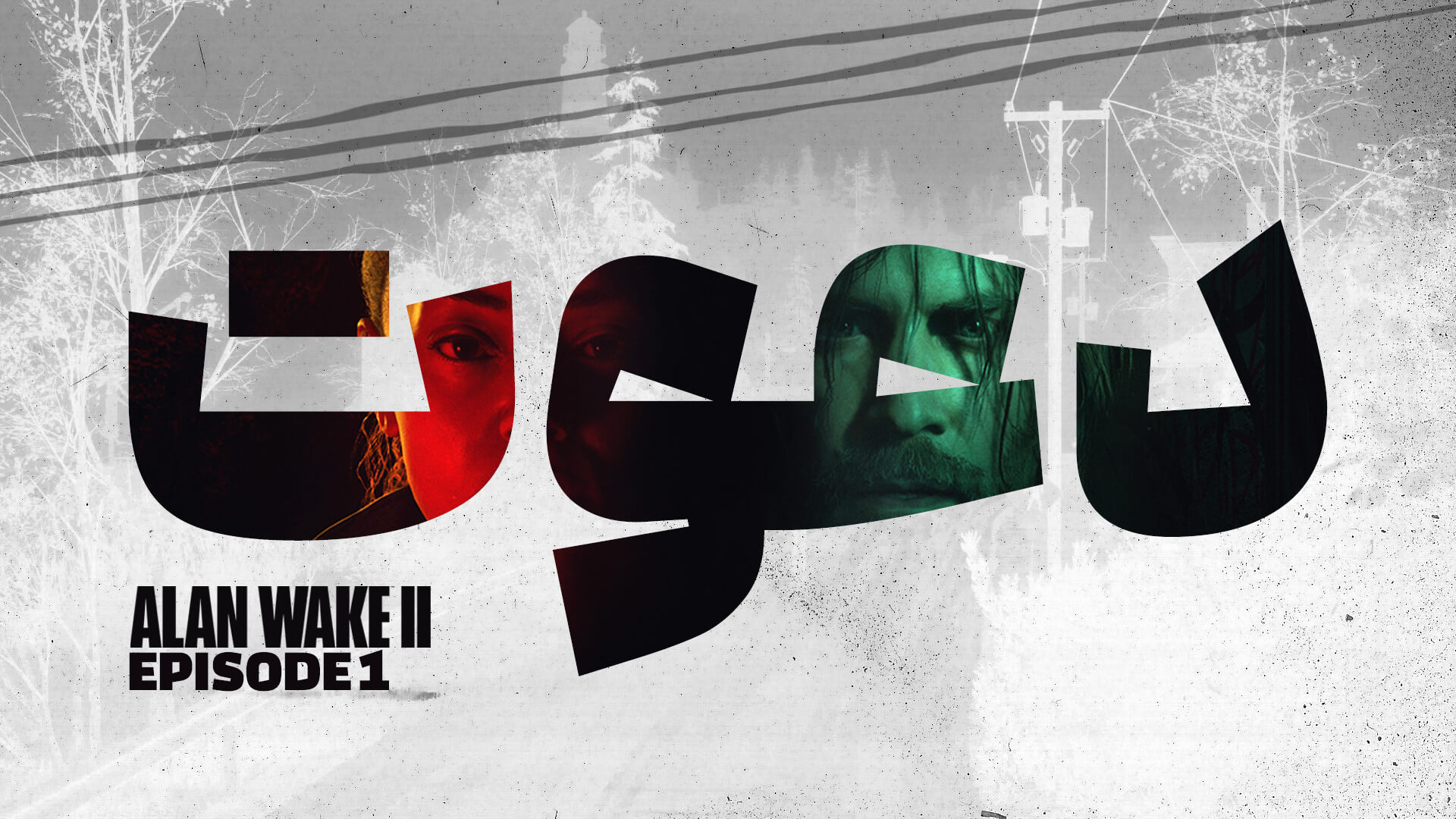
برای کانال یوتیوب کامپیوترکا KomputerKa ، فونت ادامه انتخاب شد، زیرا با لحن روایت و شخصیت محتوای کانال هماهنگی بالایی دارد. این کانال بر انتقال سریع و مستقیم پیام تمرکز دارد و به همین دلیل به فونتی نیاز داشت که بدون پیچیدگی، مفهوم را در کوتاهترین زمان ممکن به مخاطب منتقل کند.برای مثال، در اپیزود نخست با موضوع Alan Wake از کلمه «دعوت» استفاده شد. وزن و ساختار فونت ادامه باعث شد این کلمه بهسرعت دیده شود و تأثیر اولیه موردنظر را ایجاد کند. به همین دلیل، مهمترین معیار در انتخاب این فونت، توانایی آن در انتقال سریع و مؤثر پیام بود.
چه محتوای ویدئو فضایی جدی و تاریک داشته باشد و چه پرانرژی و هیجانانگیز باشد، فونت ادامه میتواند هویت بصری یکپارچه کانال را حفظ کرده و پیام را بهسرعت به مخاطب منتقل کند. نمونههای بیشتر این رویکرد را میتوان در کانال KomputerKa مشاهده کرد.
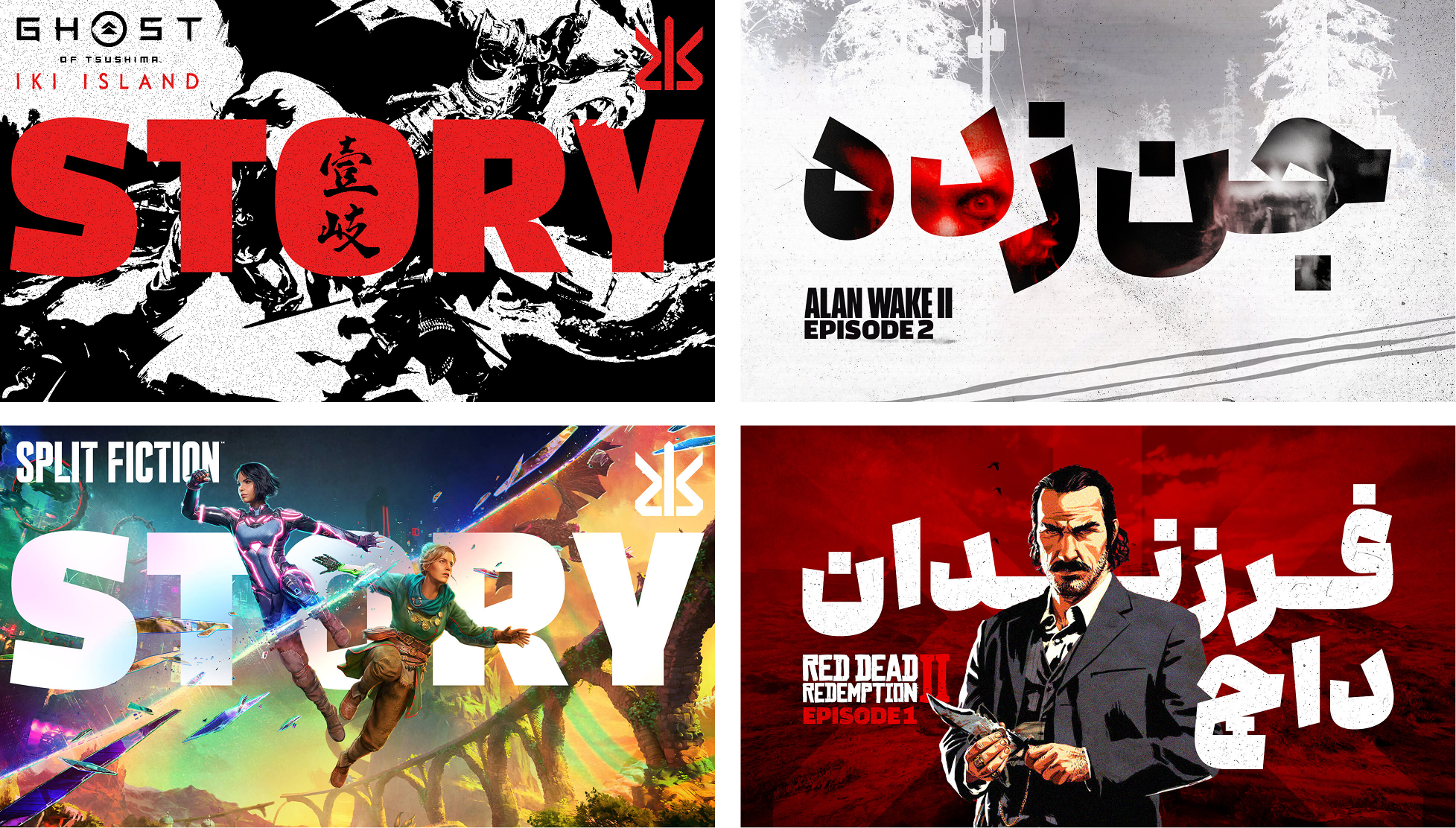
پیش از بررسی کانالهای دیگر یوتیوب، بد نیست به یک نمونه از نقش فونت در برندسازی نگاه کنیم؛ استفاده از سه فونت کلمه، انجمن، ادامه اما با موضوع بازی Alan Wake.
با وجود یکسان بودن موضوع محتوا، هر کانال با انتخاب فونت متفاوت توانسته هویت بصری مخصوص به خود را شکل دهد. این موضوع نشان میدهد که فونت، فراتر از یک ابزار نوشتاری، میتواند نقش مهمی در تعریف شخصیت و هویت یک محتوا داشته باشد.
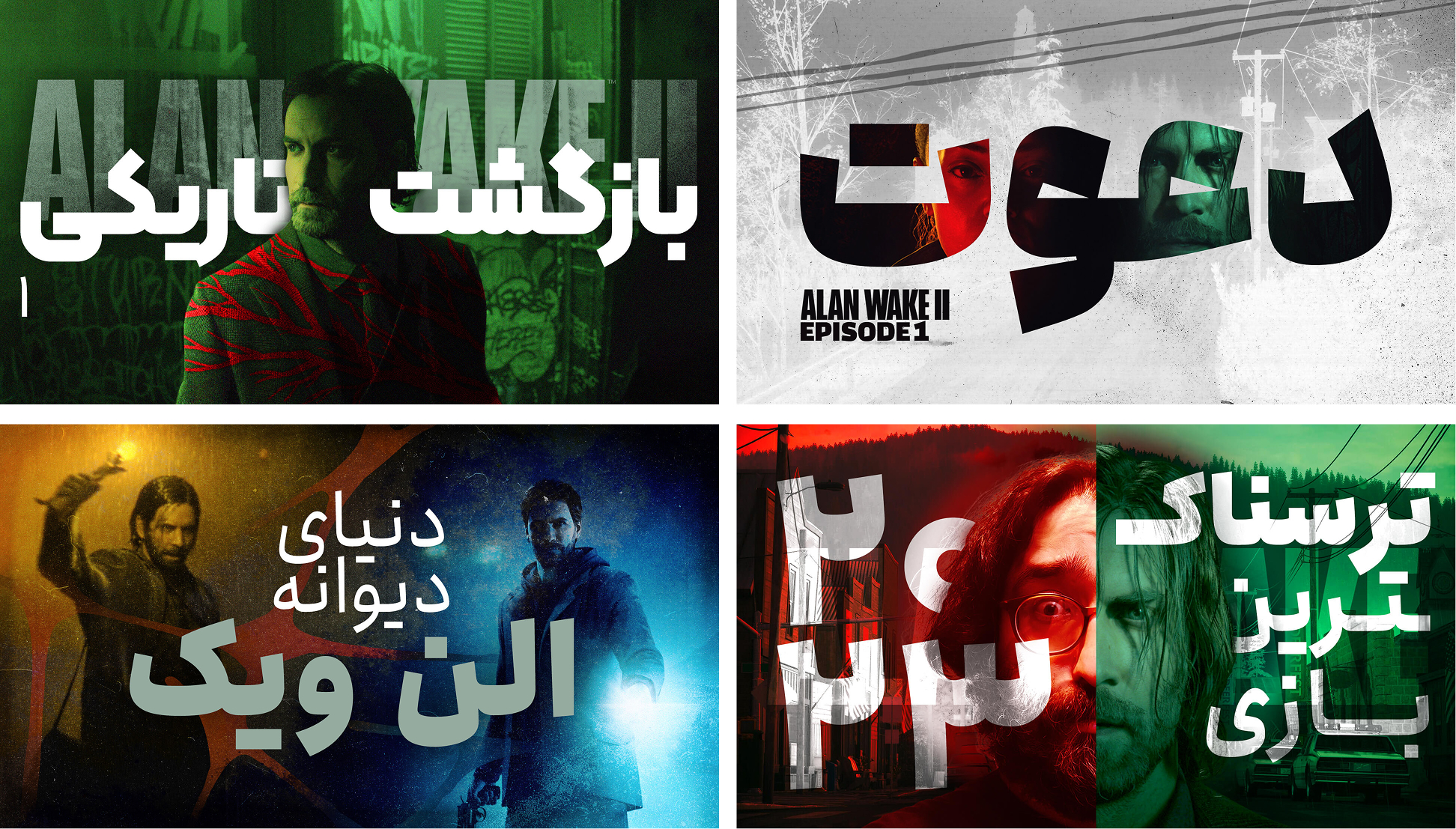
برای کانالهای یوتیوب Omid Lennon و KasraKT از فونت انجمن استفاده شده است. دلیل این انتخاب بیشتر به جنس محتوای این دو کانال برمیگردد؛ زیرا کسری کریمیطار و امید صدیقایمانی پیش از تولید محتوا در یوتیوب، سالها در حوزه نقد، مقالهنویسی و بررسی حرفهای بازیهای ویدیویی فعالیت داشتهاند.
فونت انجمن بهدلیل تنوع وزن و ساختار متعادل خود، انتخاب مناسبی برای این سبک محتواست. این فونت کمک میکند بخشهای مهم متن تأکید بیشتری بگیرند و در مقابل، بخشهای کماهمیتتر با وزن سبکتر نمایش داده شوند. در نتیجه، مخاطب راحتتر میتواند سلسلهمراتب اطلاعات را تشخیص دهد و روی نکات اصلی تمرکز کند.این ویژگی باعث شده «انجمن» علاوه بر حفظ خوانایی، با فضای تحلیلی این دو کانال نیز هماهنگی خوبی داشته باشد.
پس از بررسی و آزمون گزینههای مختلف، در همکاری با کانال یوتیوب THE PLAY MIND به این جمعبندی رسیدیم که فونت درباره بهترین انتخاب است؛ چرا که بیش از هر گزینهی دیگر، توانست فرم بصری و نگاه مدنظر ما را بهدرستی منتقل کند.
در فرآیند انتخاب فونت برای کانال یوتیوب AMIRFERY، بهدنبال فرمی بودم که بتواند بهصورت همزمان حس بازیگوشی و استحکام را منتقل کند. پس از بررسی گزینههای مختلف، فونت کلمه تنها گزینهای بود که توانست این دو ویژگی را برای ما بهدرستی در کنار یکدیگر به نمایش بگذارد.
در کانال یوتیوب Masoudbyhimself، مسعود تیموری پیش از آغاز همکاری با من، فونت دانا را بهعنوان فونت اصلی کانال انتخاب کرده بود. این انتخاب، بهدلیل خوانایی بالا و شخصیت بصری منسجم، بستر مناسبی برای توسعه هویت بصری کانال ایجاد کرد و مسیر طراحی تامنیلها را برای من هموار ساخت. در ادامه نیز با حفظ همین انتخاب، تلاش کردم انسجام بصری کانال را در تمامی طراحیها حفظ و تقویت کنم.
در نهایت، هیچ فونتی را نمیتوان بهترین گزینه برای تمامی کانالهای یوتیوب دانست. انتخاب فونت باید بر اساس نوع مخاطب، ماهیت محتوا، سبک طراحی و هویت بصری برند انجام شود. با این حال، یک اصل همواره ثابت است: موفقترین فونت، فونتی است که بتواند پیام را در سریعترین زمان، با بیشترین وضوح و مؤثرترین شکل ممکن به مخاطب منتقل کند.